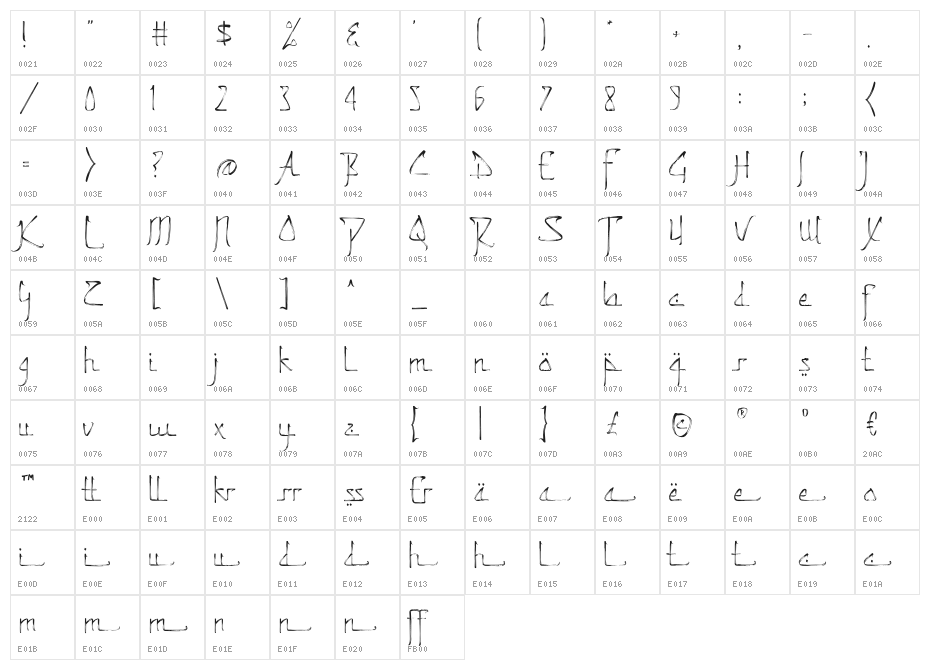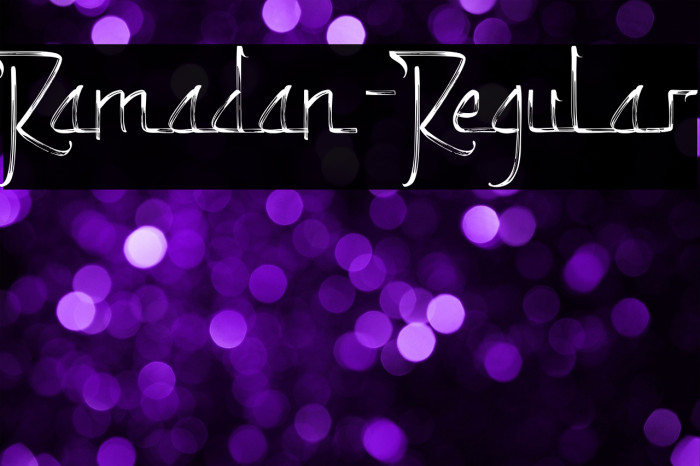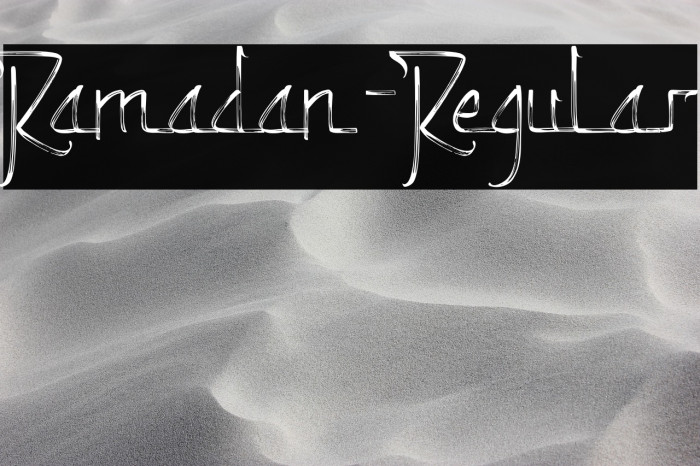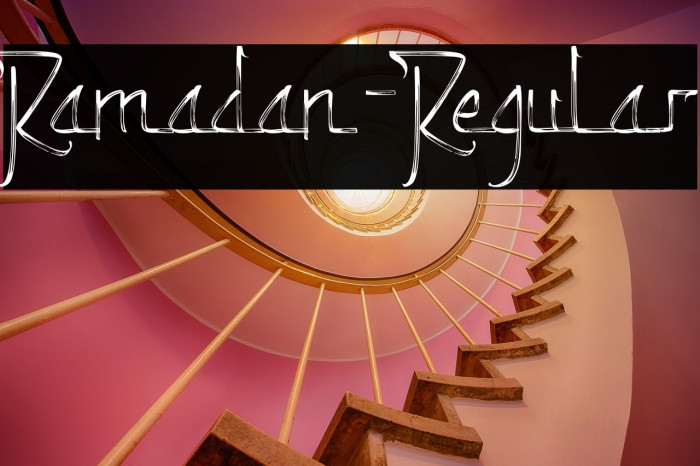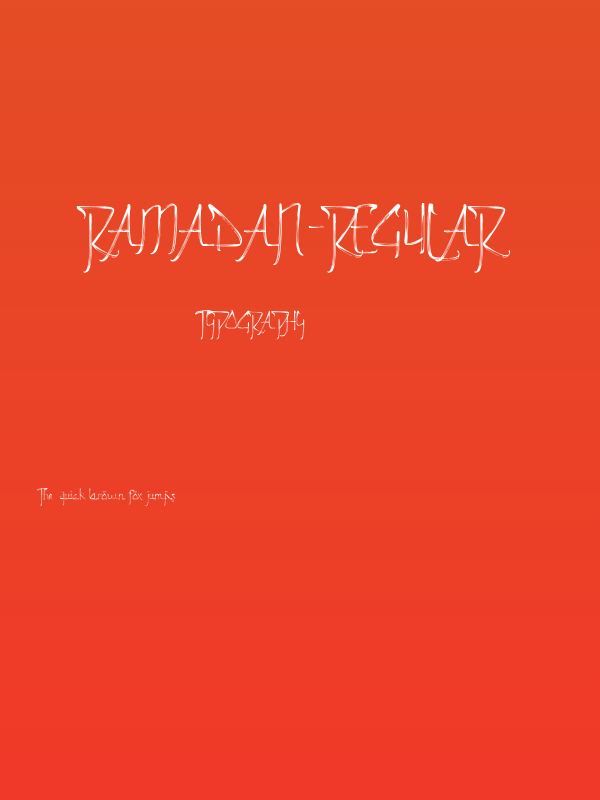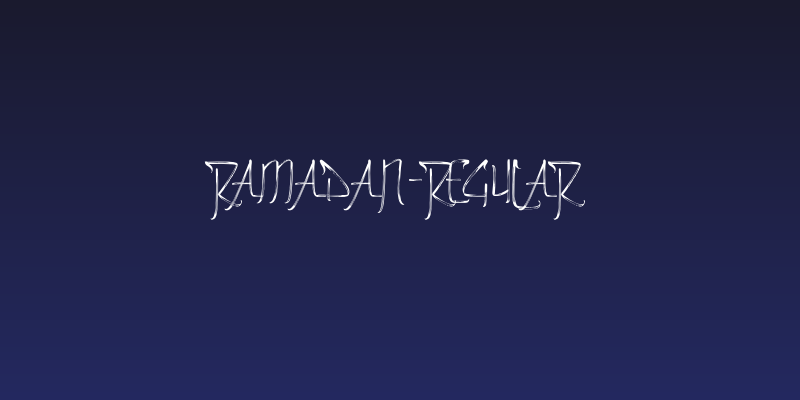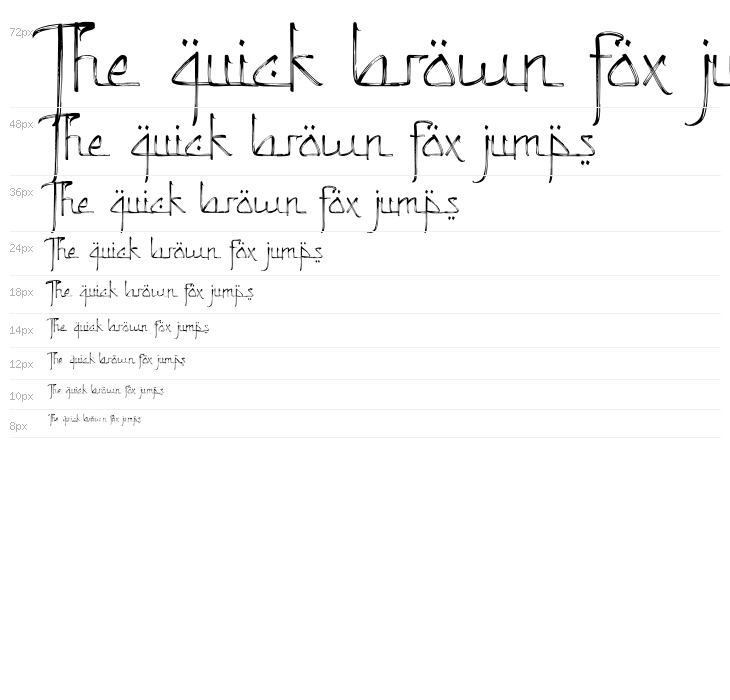
Ramadan-Regular Font
| Caso de uso | Logos, Headlines, Artistic projects |
| Proyectos propuestos | Ideal for invitations, branding, posters, and artistic projects requiring a decorative touch. |